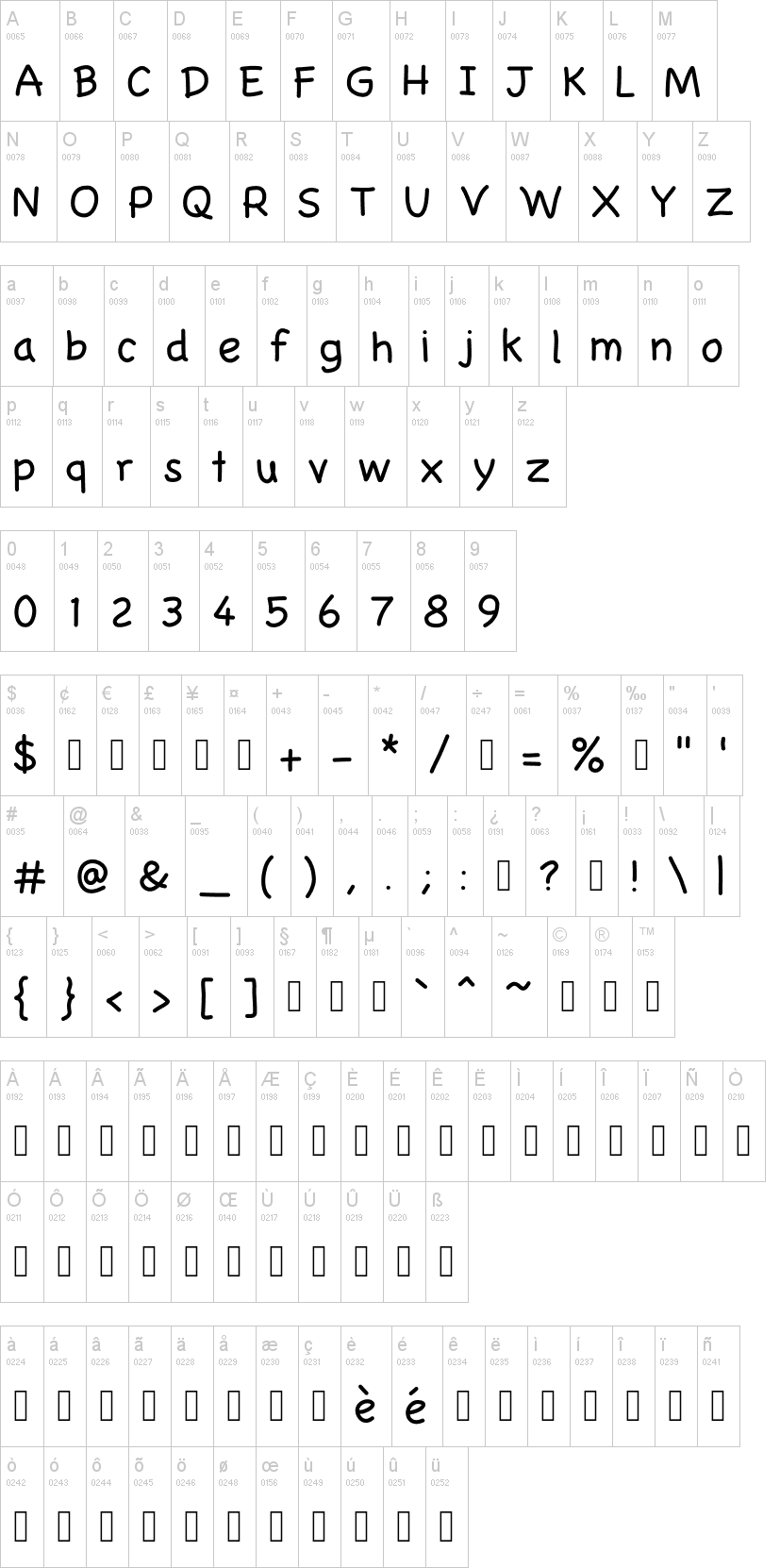
Gaelle 001
Gaelle 001 是一种现代风格的字体,它的特点是字母线条的弯曲和流畅感。这种字体由法国设计师Gaelle独立设计,于2010年发布。 Gaelle 001 字体的使用范围广泛,特别适用于广告、包装设计、名片、海报和网站等设计领域。它的字母有很多的变体和装饰,使它的设计灵活性很高。该字体还提供了多种字重和斜体版本,以满足设计师的需求。总的来说,Gaelle 001 字体是一种非常具有现代感和艺术感的字体,适合用于各种设计项目中。
Gaelle 001是一款非常不错的手写艺术字体,具有很好的视觉感,适合于文化类的宣传设计、商业类品牌的广告和产品包装设计以及个性化文字排版等较多场景。
Gaelle 001字符映射图